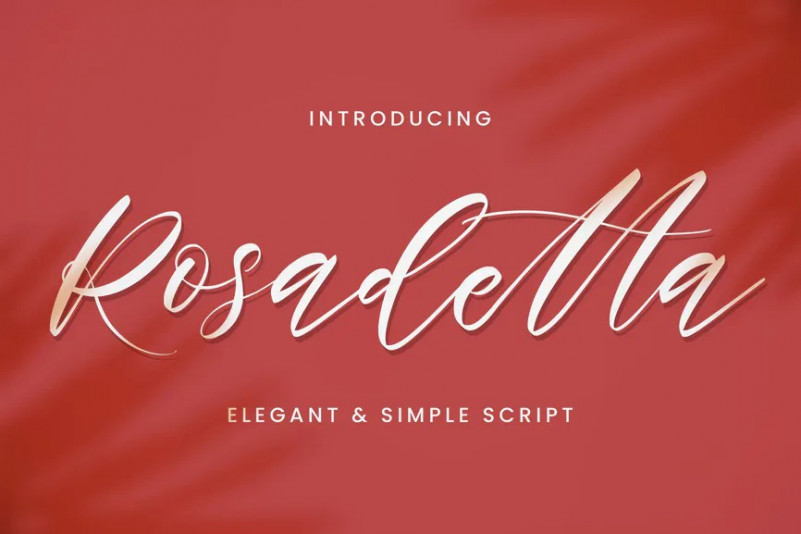
Rosadetta Font
Rosadetta est un script élégant qui se sent élégant manuscrit, et moderne. Il est parfaitement adapté à une grande variété de projets ! Cette police fait à la main rendra votre design a une belle touche naturelle pour chaque détail. Il est parfait pour tout projet de conception comme invitation, Logo, couverture de livre, artisanat ou tout autre but de conception. Il dispose également d’une multitude de caractéristiques spéciales, y compris des glyphes et des ligatures alternées.